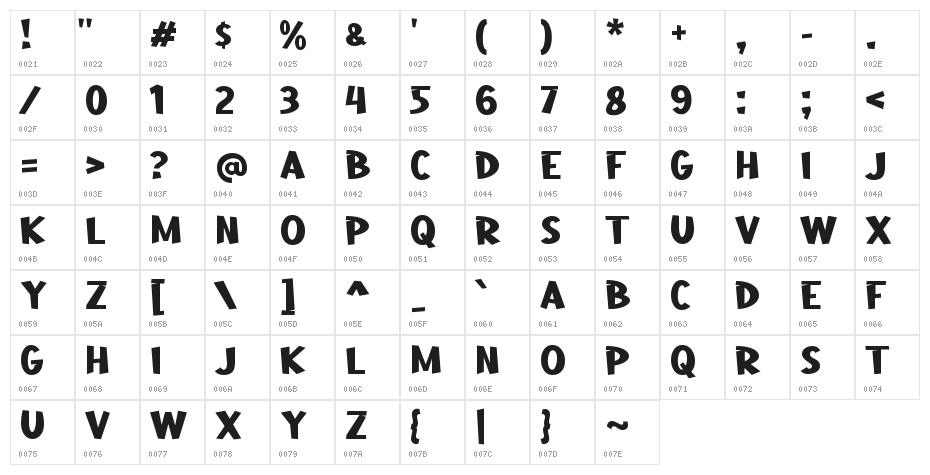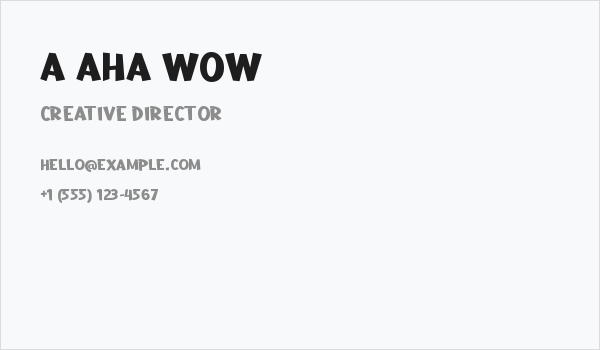
a Aha Wow Font
✎ Comic
| Stile generale | Playful, Cartoonish |
| Progetti proposti | Ideal for children's books, comic strips, playful branding, and eye-catching posters. |